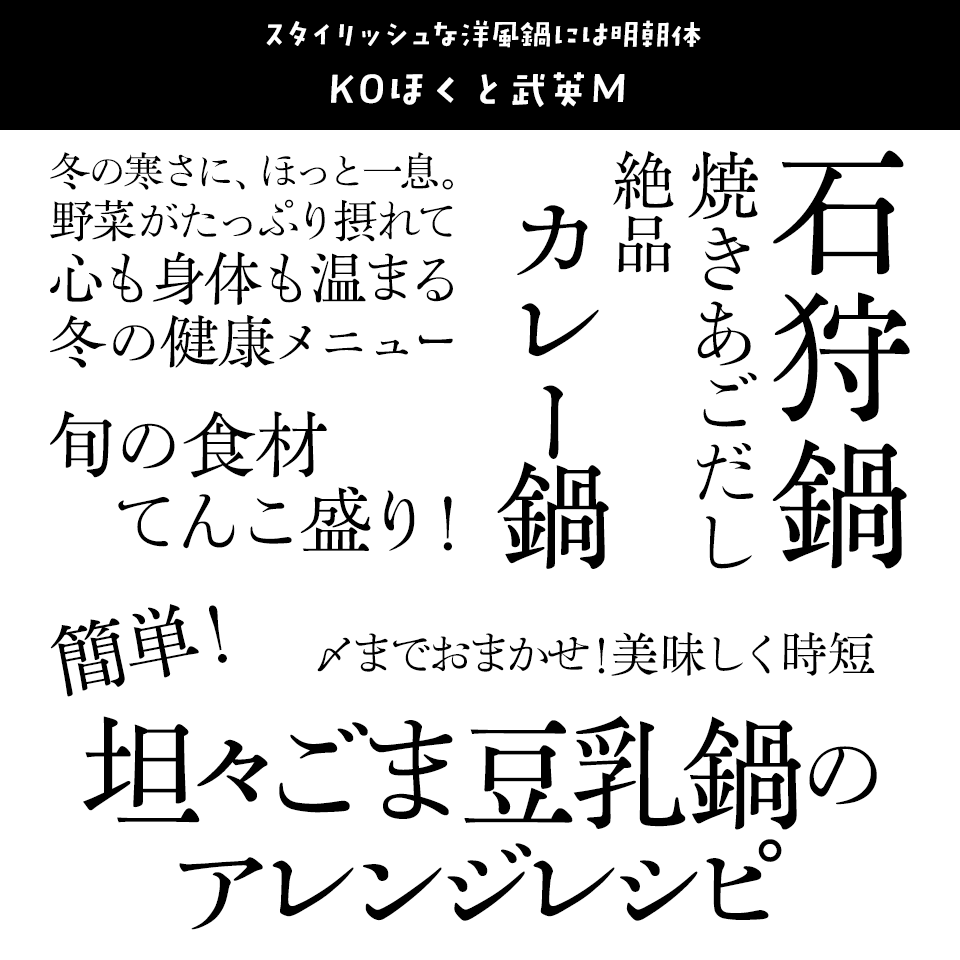
「鍋」に合うフォント だもの書体
あったかい鍋に合うほっこり可愛い筆文字フォント
だもの書体【昭和書体/コーエーサインワークス】
「鍋」に合うフォント だもの書体
書けそうで書けないへたうま書体「バサころ」の弟分。親しみやすい緩く可愛い表情を持っていますが、字形のデザインは細部にまでこだわっており、高級感や老舗感を演出することもできます。居酒屋メニューやオリジナルロゴ作成、年賀状デザインなど、様々なシーンで活躍できる毛筆書体フォントです。
「鍋」に合うフォント TAあっぱれフォントRタイプ
鍋料理にぴったりの個性派筆文字フォント
TAあっぱれフォントRタイプ【スキルインフォメーションズ】
「鍋」に合うフォント TAあっぱれフォントRタイプ
豪快にそして自由奔放に個性あふれる筆文字フォントです。
「鍋」に合うフォント 横丁&鍛所 あまからフォント
丸みがあって優しい味わいの鍋に合うフォント
横丁&鍛所 あまからフォント【六葉情報】
「鍋」に合うフォント 横丁&鍛所 あまからフォント
丸みを帯びた極太の毛筆書体で、暖かくて優しい親しみやすい印象を持っています。
「鍋」に合うフォント 魂心
力強く濃い目の味わいの鍋に合うフォント
魂心【白舟書体】
「鍋」に合うフォント 魂心
全身全霊、渾身の力を込めて書かれた魂の極太書体。
「鍋」に合うフォント 武骨
濃厚で深いコクがあるような鍋に合うフォント
武骨【白舟書体】
「鍋」に合うフォント 武骨
かすれが出る程の筆スピードで書き上げられていながら、コンパクトに四角くまとめ上げた太くたくましい字形を持ちます。看板や題名などここ一発のインパクトにふさわしい書体です。
「鍋」に合うフォント 京円
どんな鍋にも合う定番の毛筆書体フォント
京円【白舟書体】
「鍋」に合うフォント 京円
墨のにじみも上品な、京の薫りのする書体、純和風という言葉にピッタリです。奇抜さや大胆さには劣りますが、和風を意識したいロゴや題名によし、優しい文章を打つのによし、の毛筆書体です。
「鍋」に合うフォント DF大河体
豪快だけど繊細、魚介系の鍋に合うフォント
DF大河体【ダイナフォント】
「鍋」に合うフォント DF大河体
筆は鼬 (いたち) の毛の筆を使用しており、その特徴である優れた弾力性が、起筆や払いの勢いに見事に反映されると共に、流れるような筆運びにも色濃くあふれています。豪快かつ極太な筆画の中に、どことなく女性書道家らしい繊細さや柔らかさも感じさせる文字です。
「鍋」に合うフォント 筆技名人フォント 悠創体
ガッツきたくなる豪快な鍋に合うフォント
筆技名人フォント 悠創体【ミーネット】
「鍋」に合うフォント 筆技名人フォント 悠創体
インパクトのある力強い太文字が特徴の『悠創体』、第一線で活躍するプロの書家さんが一文字ずつ丁寧に書き上げた筆文字をスキャンしたアウトラインデータを元にしていますので、デジタルデータでありながら手書き筆文字独特の温かみのあるフォントとなっています。
「鍋」に合うフォント 筆技名人フォント 春雲体
おでんやあっさり白出汁系鍋に合うフォント
筆技名人フォント 春雲体【ミーネット】
「鍋」に合うフォント 筆技名人フォント 春雲体
毛筆独特の「にじみ」が強調された『春雲しゅんうん体』は、使いやすい楷書をベースに、なるべく「角」をなくして丸みをつけることで柔らかい印象に仕上げました。キャッチコピーやロゴへの使用はもちろん、文章などの小さめの文字でも読みやすいよう工夫してありますので、用途を選ばず利用できる書体です。
「鍋」に合うフォント 髭筆フォントシリーズ 爆天書体-旺-
あっつあつの鍋を表現できる豪快な筆文字フォント
髭筆フォントシリーズ 爆天書体-旺-【Design筆文字Font】
「鍋」に合うフォント 髭筆フォントシリーズ 爆天書体-旺-
筆文字職人・墨人爆天が描いた書体。豪快な筆致でありながら、温もりと優しさを有した人情味ある書体に創り上げています。
「鍋」に合うフォント 手書き屋本舗 TAw-太郎
魚介類,野菜がたっぷりの寄せ鍋に合うフォント
手書き屋本舗 TAw-太郎【ウェブフォントジャパン】
「鍋」に合うフォント 手書き屋本舗 TAw-太郎
温かみのある表情で、読む人の目をデザインの重要なポイントに引きつけ、筆文字の雰囲気を醸し出しています。1つの文字の中で、ストロークの幅が変化したり、ストロークの流れが反対になったり、場合によっては 1つの文字が一筆書きで書かれたりすることもあります。
「鍋」に合うフォント TA江戸文字
ちゃんこ鍋に合う相撲体フォント
TA江戸文字【スキルインフォメーションズ】
「鍋」に合うフォント TA江戸文字
やや長体がかかった力強い毛筆書体で江戸文字の中でも根岸流(相撲字)に近いデザイン。ちゃんこ鍋に最適なフォントです。
「鍋」に合うフォント 熊ちゃん体
ほっこりやさしい手書きフォント
熊ちゃん体【楽フォント】
「鍋」に合うフォント 熊ちゃん体
カジュアルでスマートな感じの面相で描いています。筆画は一致しており、子供っぽさとかわいらしさを失うことなく、人々に無邪気さと輝きの感覚を与えながら強い視覚的魅力を持っています。
「鍋」に合うフォント DF唐風隷書体
キムチ鍋や麻婆鍋など辛めの鍋に合うフォント
DF唐風隷書体【ダイナフォント】
「鍋」に合うフォント DF唐風隷書体
横長で太く扁平な字形がどっしりと落ち着きを感じさせる「隷書体」です。
「鍋」に合うフォント DSくるみるく
トマト鍋など洋風鍋にぴったりのフォント
DSくるみるく【七種泰史/デザインシグナル】
「鍋」に合うフォント DSくるみるく
ゴロゴロ、ホロホロ。ふっくら、ほっこり。不揃いの中にも味のある書体です。温かみのあるデザインがほっかほかの鍋にぴったりのフォントです。
「鍋」に合うフォント TMコッペパレット
もつ鍋などコラーゲンたっぷりの鍋にあうフォント
TMコッペパレット【タンデムフォント】
「鍋」に合うフォント TMコッペパレット
ぷるぷる、ポムポムした印象の太い書体を目指し、細部まで考えて作られたデザイン書体です。ふんわり・ぽってりして動きのある太めのTMコッペパレットは、見出しや、テロップなどに最適です。
「鍋」に合うフォント タカスマイル丸 DB
温かみのある鍋料理の紹介に最適なフォント
タカスマイル丸 DB【タカ書体】
「鍋」に合うフォント タカスマイル丸 DB
「タカスマイル丸 DB」は、柔らかな丸みと親しみやすいデザインが特徴のフォント。変化に富んだ楽しくて可愛い字形が具沢山の鍋を紹介するときにぴったりです。
「鍋」に合うフォント KOほくと武英M
スタイリッシュな洋風鍋には明朝体
KOほくと武英M【欣喜堂】
「鍋」に合うフォント KOほくと武英M
『新考北海道史』(奥山亮著、北方書院、1950)の本文書体から復刻した和字ニュースタイルの書体「ほくと」に、中国・清代の康熙帝・雍正帝の時代に銅活字を用いて作られた『古今図書集成』(1726)から復刻した過渡期明朝体「武英」、18世紀にイギリスのジョン・バスカーヴィル(1706~ 1775)が製作した活字が用いられている『田園詩と農事詩』(1757)から復刻したトランジショナルローマン体「K.E.Cancer Medium」を組み合わせた日本語書体です。